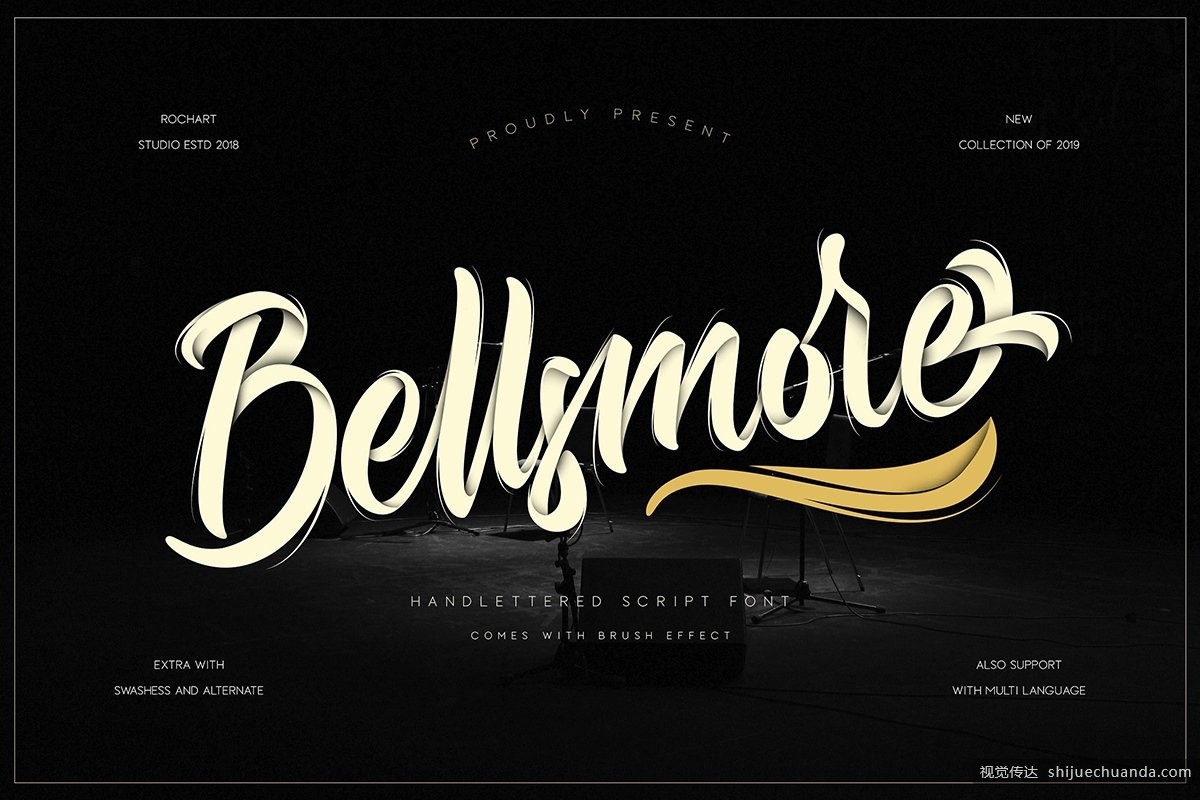
漂亮的手写笔刷英文字体 Bellsmore Brush Script
Bellsmore笔刷手写字体是一种包含更多替代和一些swashess的字体。这种字体旨在相互补充使用。Bellsmore笔刷脚本非常适合徽标设计,T恤,传单,服装,包装,广告,婚礼邀请等。此字体包含大写,小写,替代,数字,符号,标点符号,连字和奖金花饰。还支持多语言和已经PUA编码。